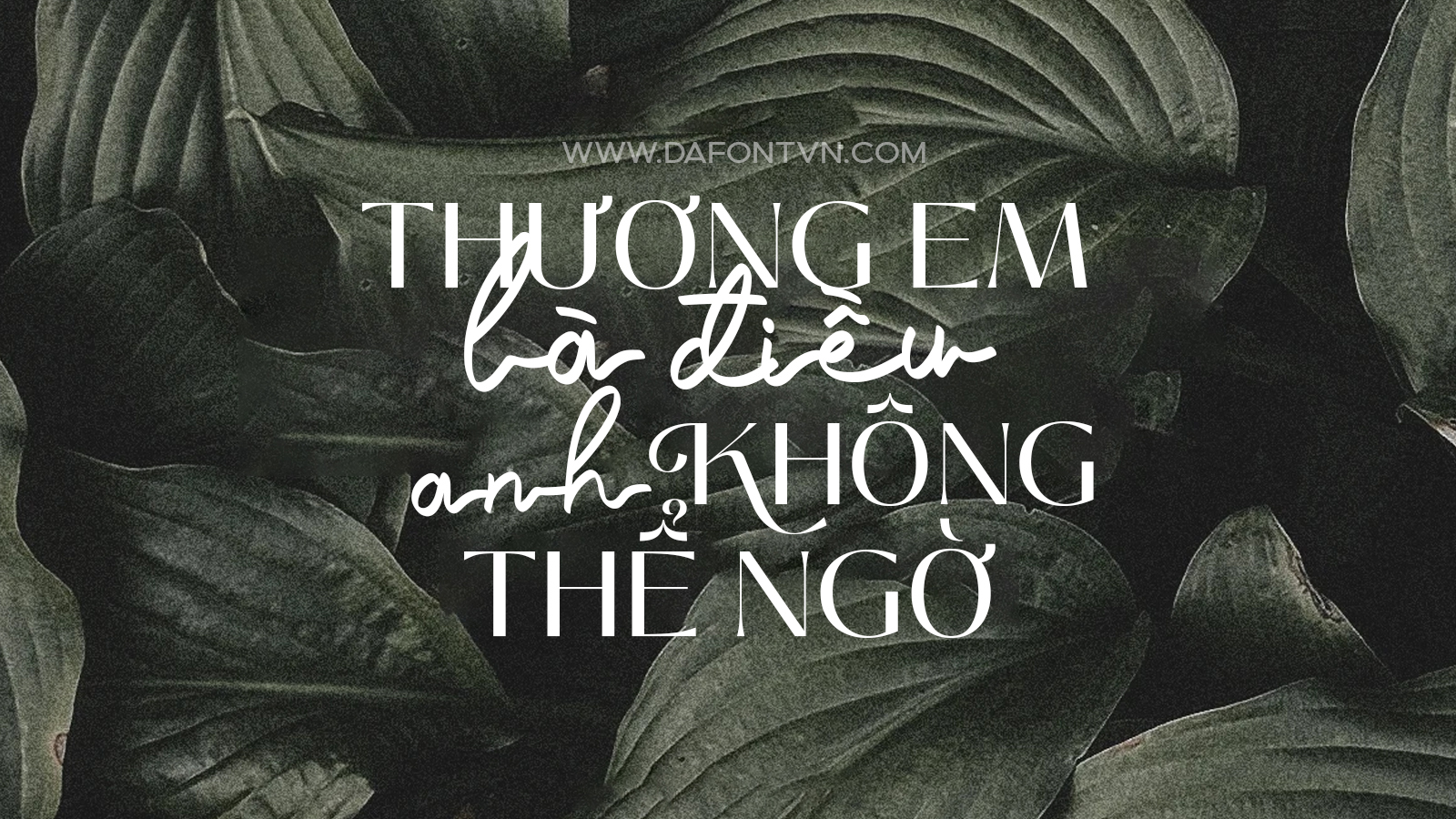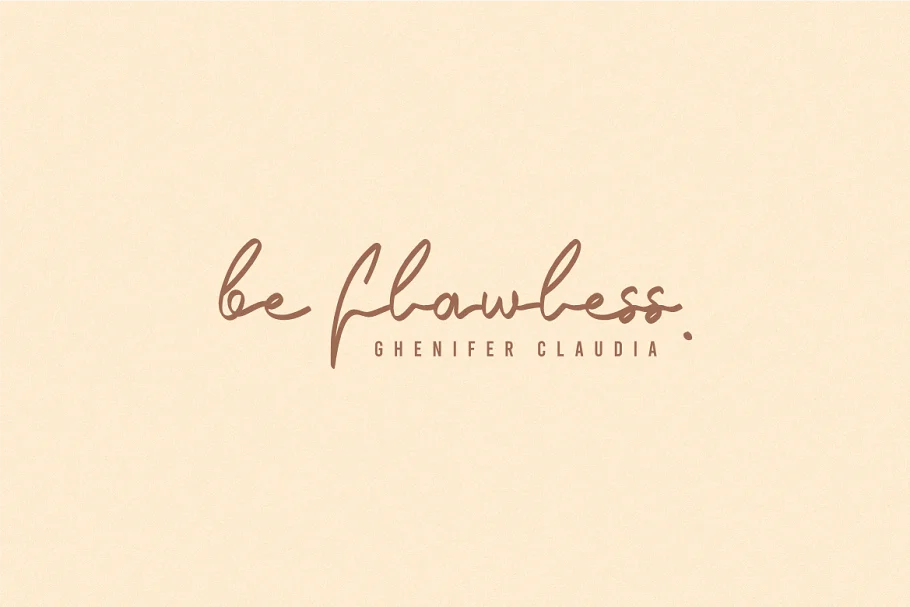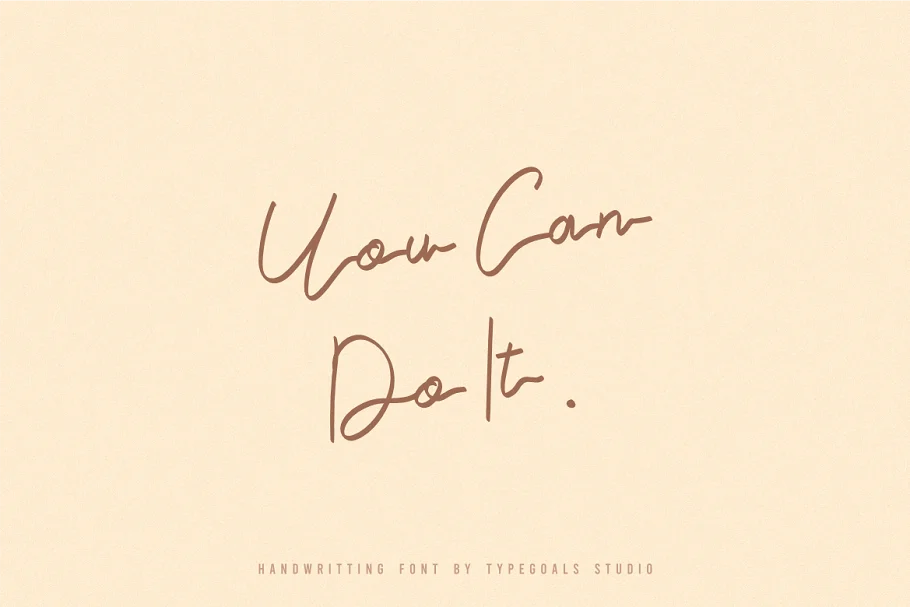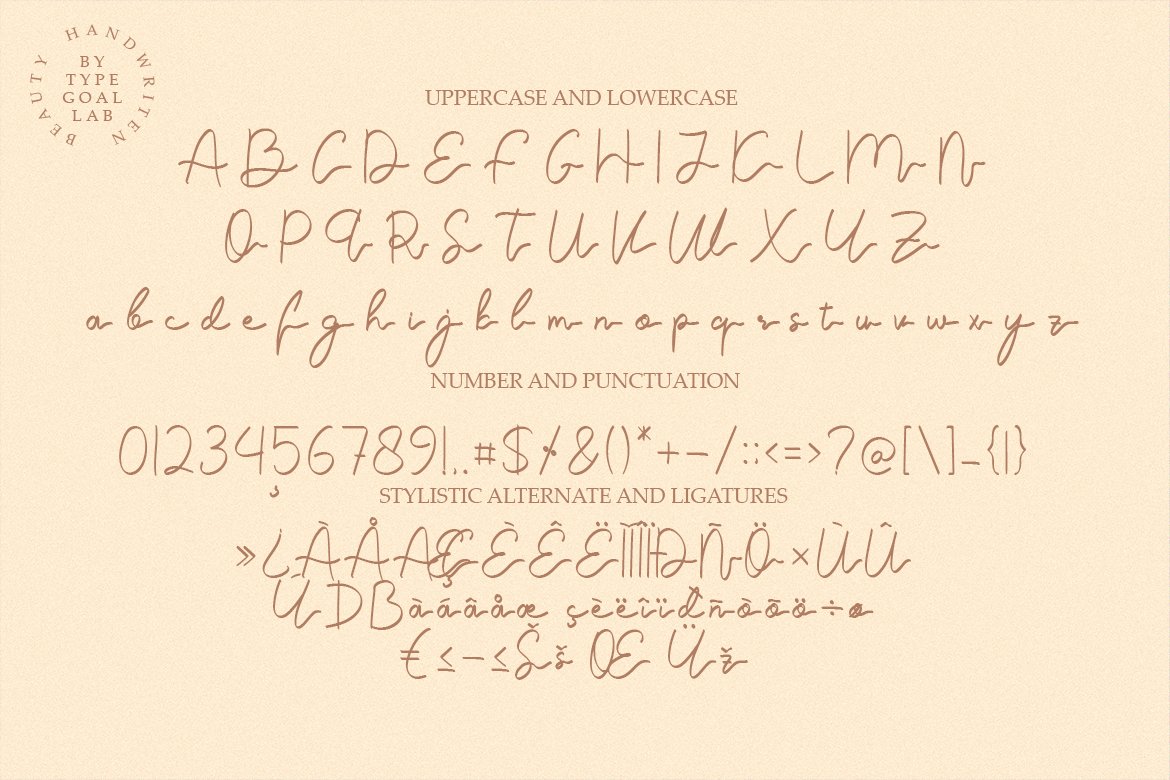
[Script] Font Ghenifer Claudia Việt Hóa
Ghenifer Claudia Font Việt Hóa – là một font chữ viết tay với một thiết kế độc đáo mang đến điểm nhấn của riêng nó và những nét mực thanh lịch. Phông chữ viết tay Ghenifer Claudia hoàn hảo cho các dự án xây dựng thương hiệu, logo, thiệp đám cưới, quảng cáo, bao bì sản phẩm, thư mời…
Font Việt Hóa đầy đủ bởi DafontVN, mình đã chỉnh sửa lại một chút, kerning và tối ưu lại để sử dụng trên cả điện thoại và máy tính.